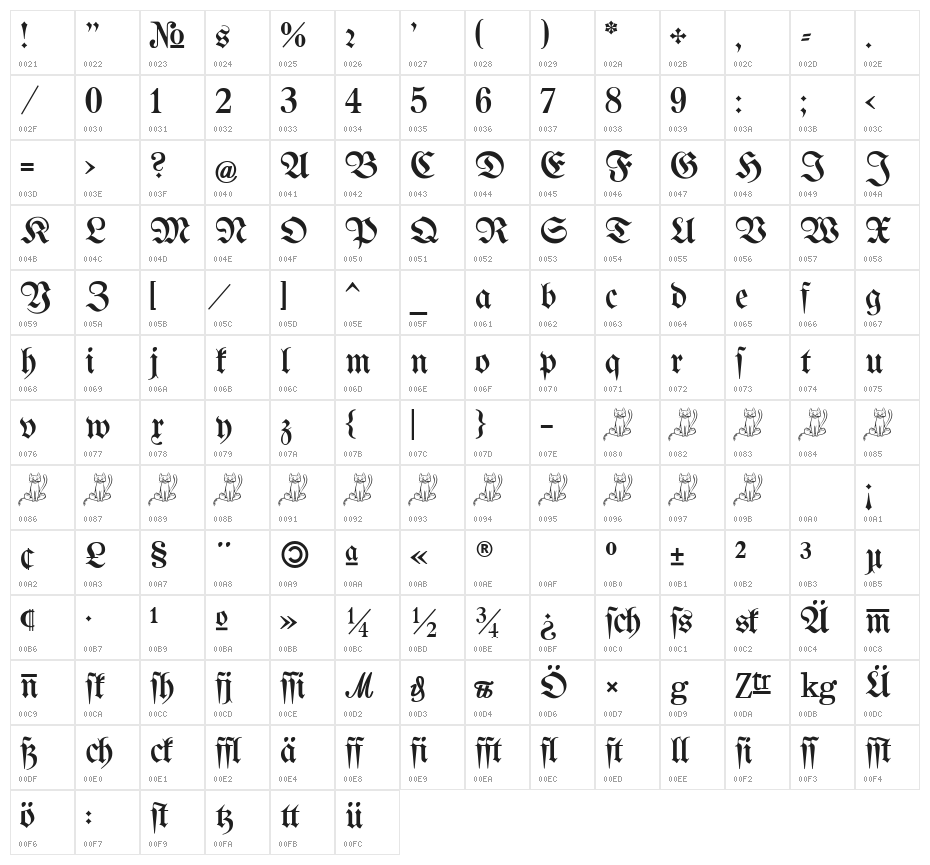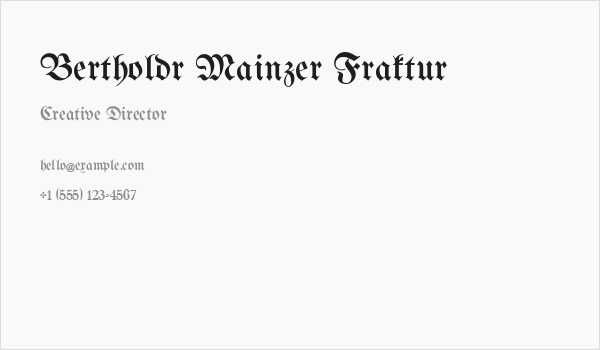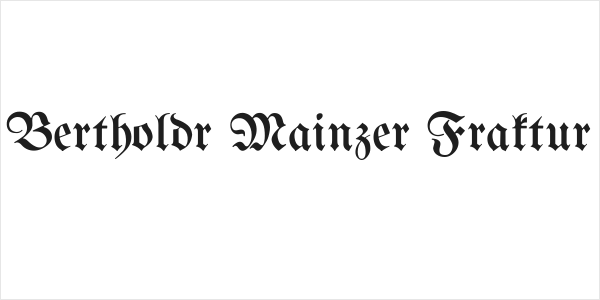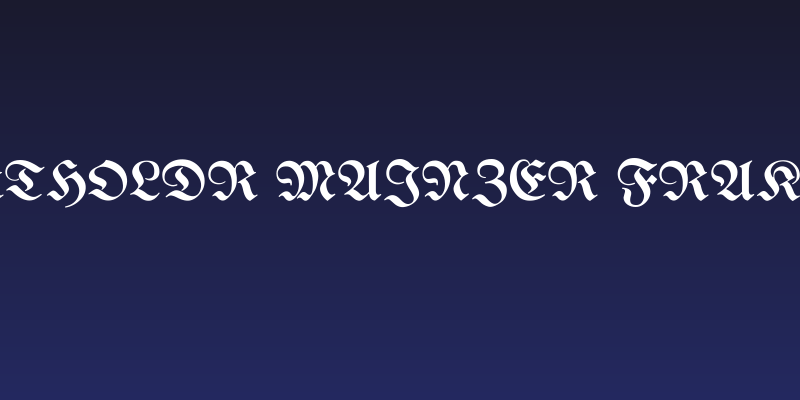
Bertholdr Mainzer Fraktur Font
| 名称 | Bertholdr Mainzer Fraktur |
| 分类 | Gothic |
| 整体风格 | Vintage |
| 使用场景 | Headlines, Logos, Decorative purposes |
| 推荐项目 | Ideal for projects requiring a historical or traditional touch, such as certificates, invitations, book covers, and branding for luxury products. |